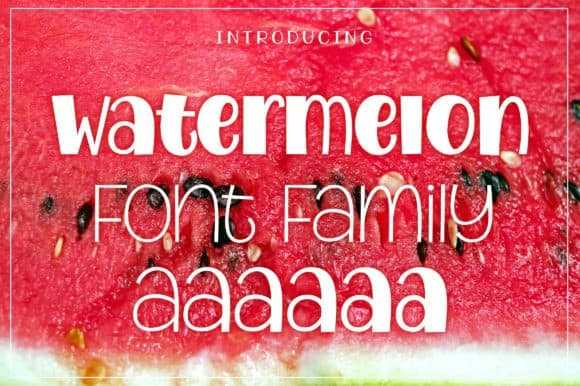
A Watermelon Display Font é uma fonte feita à mão simples que dá ao seu projeto um look divertido e jovial. Ela foi criada pelo designer Royaltype através do site 99designs. Esta fonte de destaque traz elementos frescos, fresquinhos e com sabor, capaz de transformar qualquer design em algo único e vibrante. Seus traços fortes são perfeitos para estilos modernos e criativos. Perfeito tanto para ser usado sozinha quanto misturada com outros tipos de fontes para criar um impacto visual impressionante, a Watermelon Display Font é uma ótima escolha para quem quer dar vida à sua identidade visual. Com seu sabor único e açucarado, ela se destaca na web e em materiais impressos como cartões de visita, revistas ou sites pessoais. Além disso, a fonte vem acompanhada por um conjunto de ilustrações que são perfeitas para complementar suas criações, tornando-as ainda mais memoráveis e atraentes.